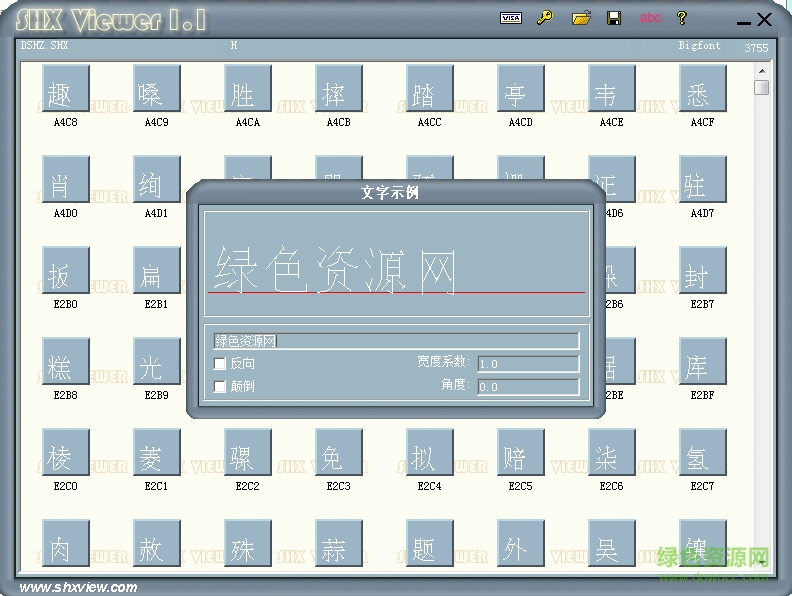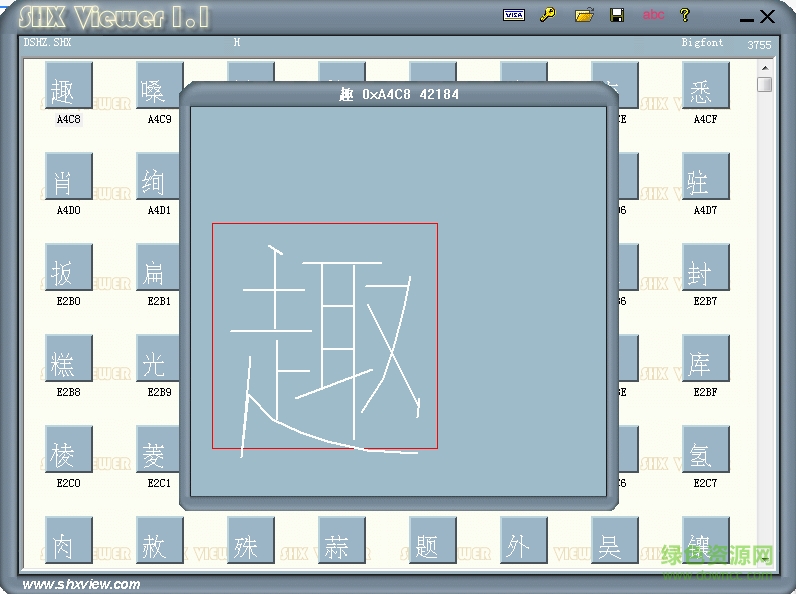
dshz.shx是一款擁有3755個(gè)漢字的cad大字體,字形簡潔偏小,連貫醒目,有著清晰的識(shí)別性和舒適的閱讀體驗(yàn),喜歡的朋友來綠色資源網(wǎng)免費(fèi)下載吧!
DSHZ.SHX字體介紹
DSHZ.SHX是常見的cad字體,支持中文輸入,字體庫比較豐富,字形大方娟秀有著極佳的書寫美感,適用于平面設(shè)計(jì)、文字標(biāo)記等諸多方面。